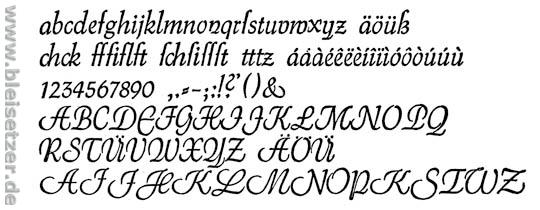
Font zum Thema Süditalien / Amalfitana / Agriturismo
ich habe unlängst oberhalb der Steilküste der Amalfitana ein Bauernpaar kennen gelernt, das ein kleines Agriturismo im Stil der ärmlichen Bauerndörfer fernab der mondänen Orte betreibt: Unverputzt, mit altem Baumbestand, Pizzaofen, Brunnen, natürlich ohne Baugenhmigung über etwas Älterem hingestellt, aber mit phantastischem Ausblick auf das Meer. Webseite und Visitenkarte gestalte ich nunmehr neu, da vorige Word 97-Entwürfe grausam sind, und die guten Menschen mich um Abhilfe gebeten haben.
Als Rahmen habe ich mich nunmehr für den unverputzten Fensterrahmen entschieden, in den Text und Bild eingefügt werden. Über der Oberseite ragt die Textur der Decke hervor. Darüber ist nochmals Raum.
In diesen Raum soll eine Wortmarke, für die ich einen geeigneten Font suche.
Hierfür suche ich einen Font, der
a) nicht zu hoch ist
b) keine zu auschweifenden Minuskeln hat
c) Italien-affin ist
d) schwungvoll wie ein wenig romantisch ist
e) trotz Schwung nicht zu zierlich und damit gut lesbar ist
Vielleicht fällt ja hier jemanden spontan ein entsprechender Font ein. Da dies ein Non-Profi(t)-Projekt ist, habe ich allerdings nicht die Mittel für einen teuren Schnitt. Ich habe allerdings im Rahmen der Universität Zugriff auf Linotype und Adobe-Fonts und noch ein paar andere.
Bisher versucht habe ich es mit Handwriting-Fonts, die ob ihrer Linienstärke allesamt nicht überzeugten sowie mit Script-Fonts und einigen Antiquas in Kursiv, die aber zu wenig "Stimmung" bieten, bzw. bei Kursiv zu gekünstelt/maniriert wirken.
Wie soll ich's ausdrücken: Ich suche einen Font für eine italienische Kulturlandschaft, der aber nicht hoch ausfallen darf.
Hmm, danke für die umfassende Beschreibung, perfekt wäre es noch gewesen den Namen der Wortmarke anzugeben, da das die Suche erleichtert.
Bei den kommerziellen Fonts habe ich mir das offensichtlich italienaffine weggedacht und versucht »schwungvoll«, »nicht-zu-zierlich«, »nicht-zu-hoch« zu beherzigen und bin (mit dem gedachten Display-Wort »Italien«) wieder einmal bei Jason Walcott gelandet; und da besonders bei Cinammon Roll, Periwinkle und, ja, auch bei Funny Bone. Die Stichworte Sudtipos, Rob Leuschke oder Ronna Penner werfe ich in der Kategorie schwungvolle Kalligraphie noch ein.
Im Free-/Shareware-Sektor*) lege ich besonders jene ans Herz:
Kontor Display von Matthias Ribeaucourt (besonders das r ist sehr schön gelungen)
Little Lord Fontleroy von Nicks Fonts (als Inlineversion) oder Fontleroy Brown (als Filledversion)
Ray Larabies Bullpen als Reminiszenz an italienische Espressocafes des letzten Jahrhunderts.
Aber auch einfach – ganz was anderes – die weich anmutende Raspoutine von Dimitri Castrique als harmonische Italicversion einer serifenlosen.
Kein Script, kein „etwas besonderes“–
Wir haben letztes Jahr für eine Online-Werbung für ein Ferienhaus in Süditalien die Warnock Pro genommen.
Die Warnock Pro von Adobe hat „unendlich“ viele Schriftschnitte, von caption, (also mit einer höheren x-height, etc.), bis display (für very big, mit großem Strichkontrasten und enger gesetzt). Besitzt grundsätzlich schöne Italics. Und kann weniger „rundlich“ daherkommen, als vergleichbare Renaissance-Antiquas.
Vielleicht bringt dir das etwas.
Falls Euch die Wortmarke bei Euren Tipps zusätzlich beflügeln sollte, die Unterkunft heißt:
"Capo la Vigna"
Herzliche Grüße an das Forum,
rakader
Hallo Rainer,
Ich habe sie mir einmal angeschaut und erlaube mir mal als Laie eine Kommentierung. Der Schwung der Bögen nach links nimmt meinem Dafürhalten v.a. bei der Cinammon Roll Schwung raus und assoziiert mit den leicht nach links geneigten Vertikalen eher eine leicht destruktive, abwartende Haltung; die Periwinkle ist mir zu statisch, inaktiv. Funny Bone ist gewöhnungsbedürftig, hat aber etwas. Leider auch hier die nach links abffallenden Vertikalen. Nun ja - und für mich schlicht zu teuer.
Etwas verspielter und schwärzer die Eckmann:
Gracie mille! Das ist ein Aspekt, den ich bisher nicht berücksichtigt hatte. Dein Vorschlag eröffnet neue Perspektiven, die mir auf Anhieb gefallen. Die Verbindung Jugendstilschriften stimmt absolut: Wird bei hochwertigen Lebensmitteln wie Marmeladen, Likören, lokalen Kaffeesorten (Maresca - mein Tipp aus Sorrento) dort gerne und oft verwendet, v.a. dort, wo Tradition und la manifattura assoziiert werden soll.